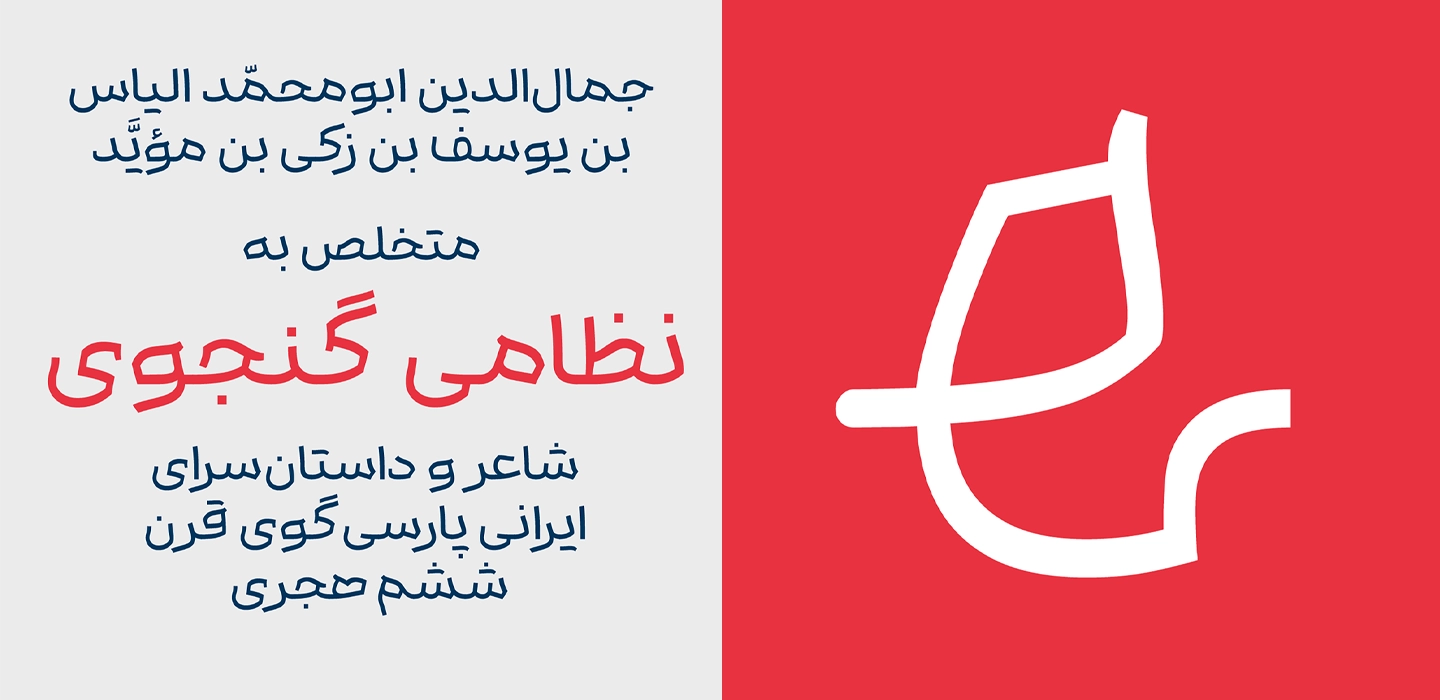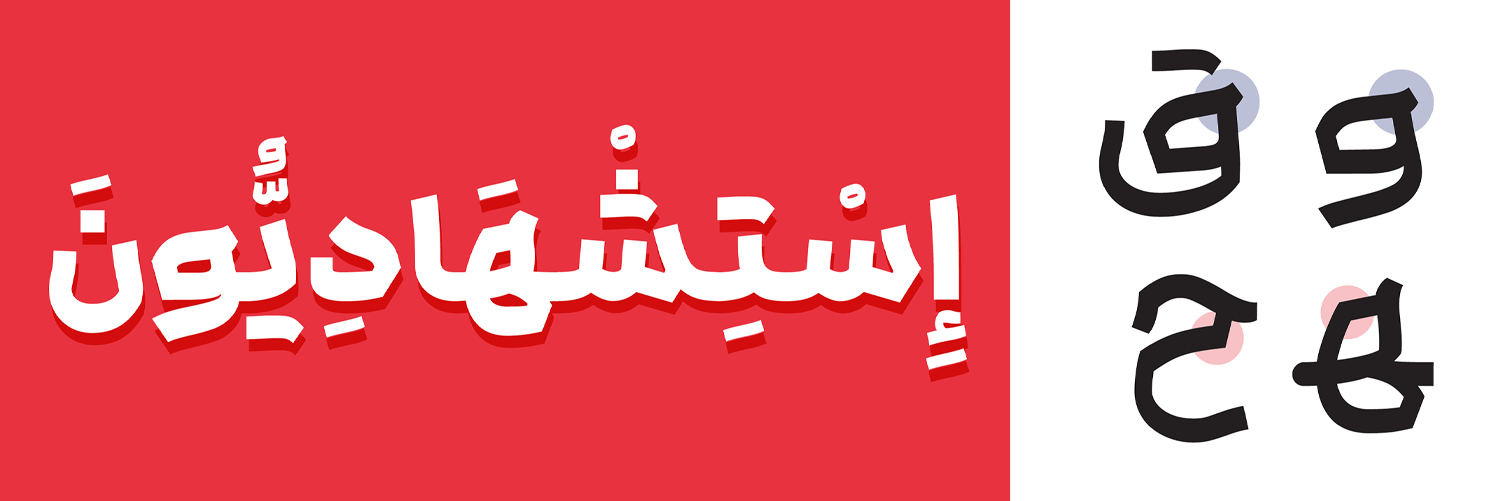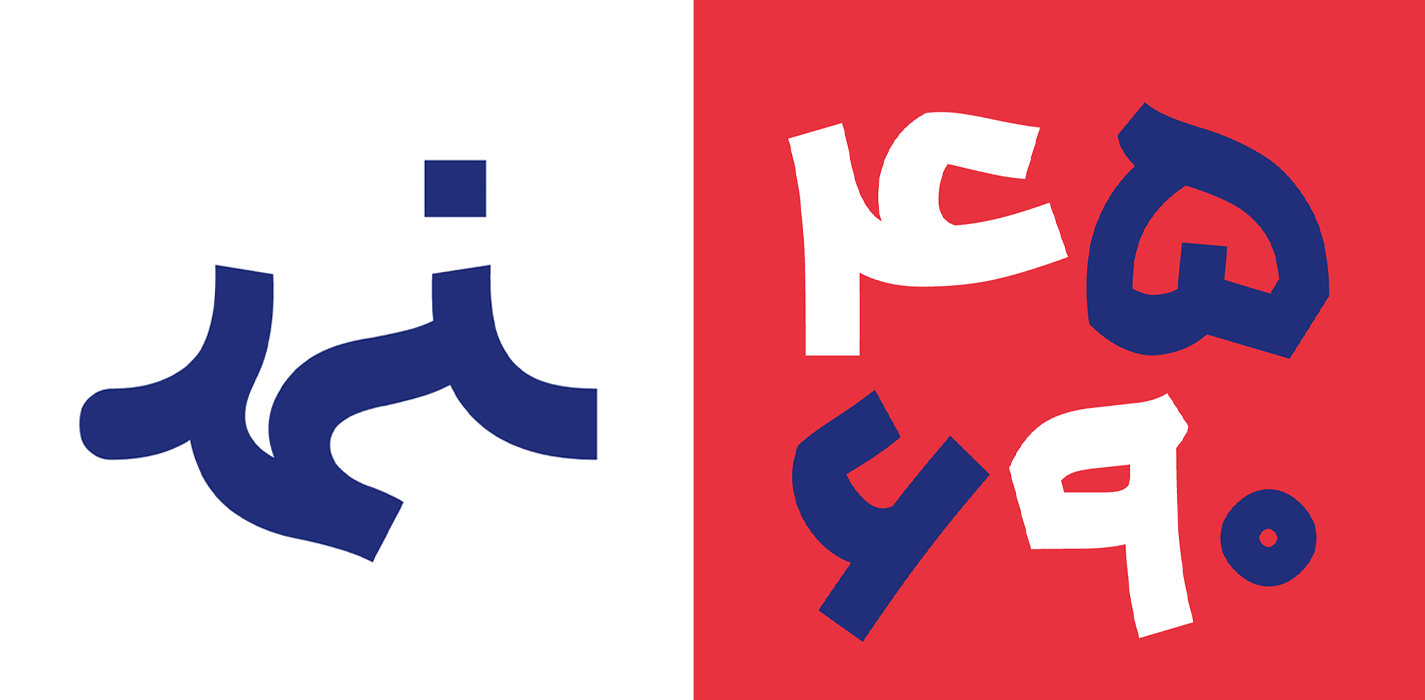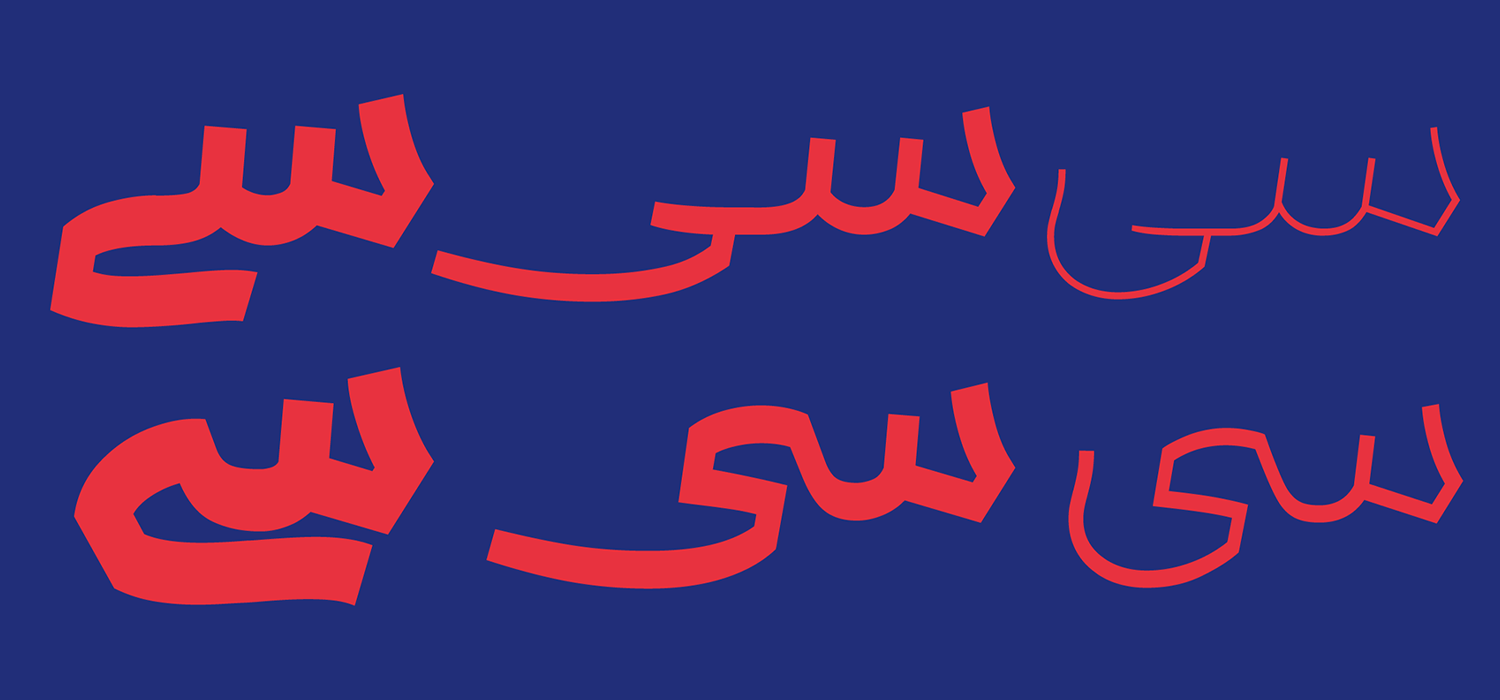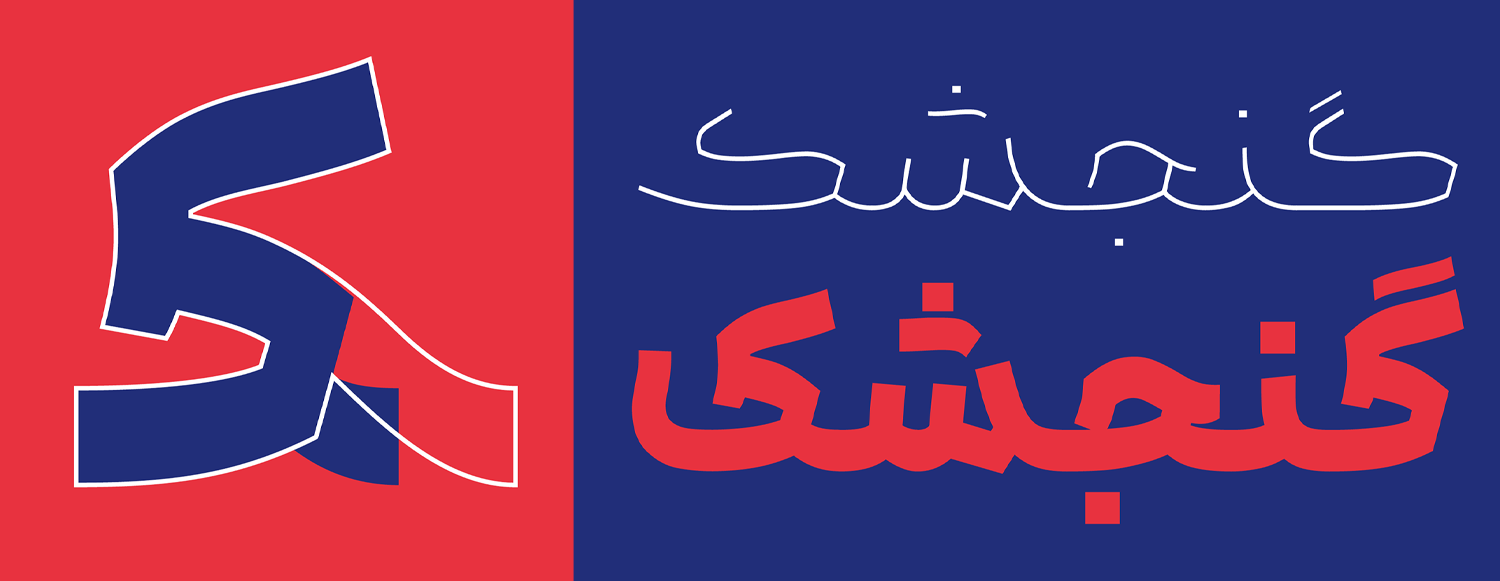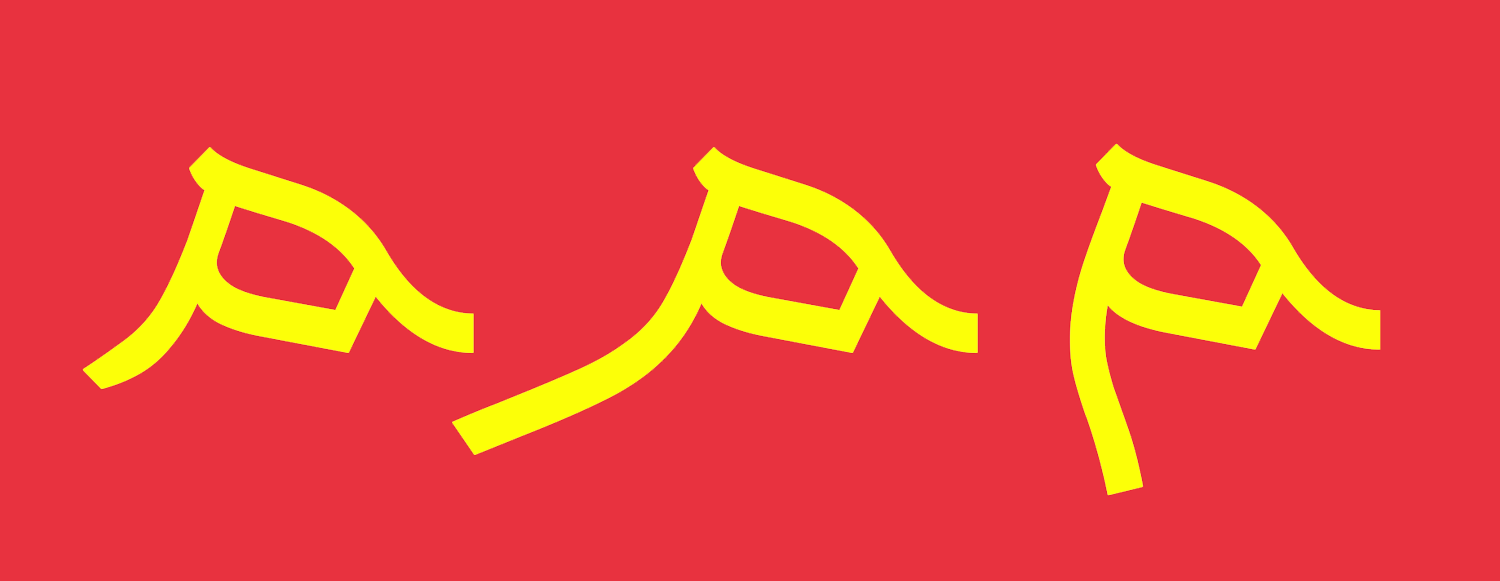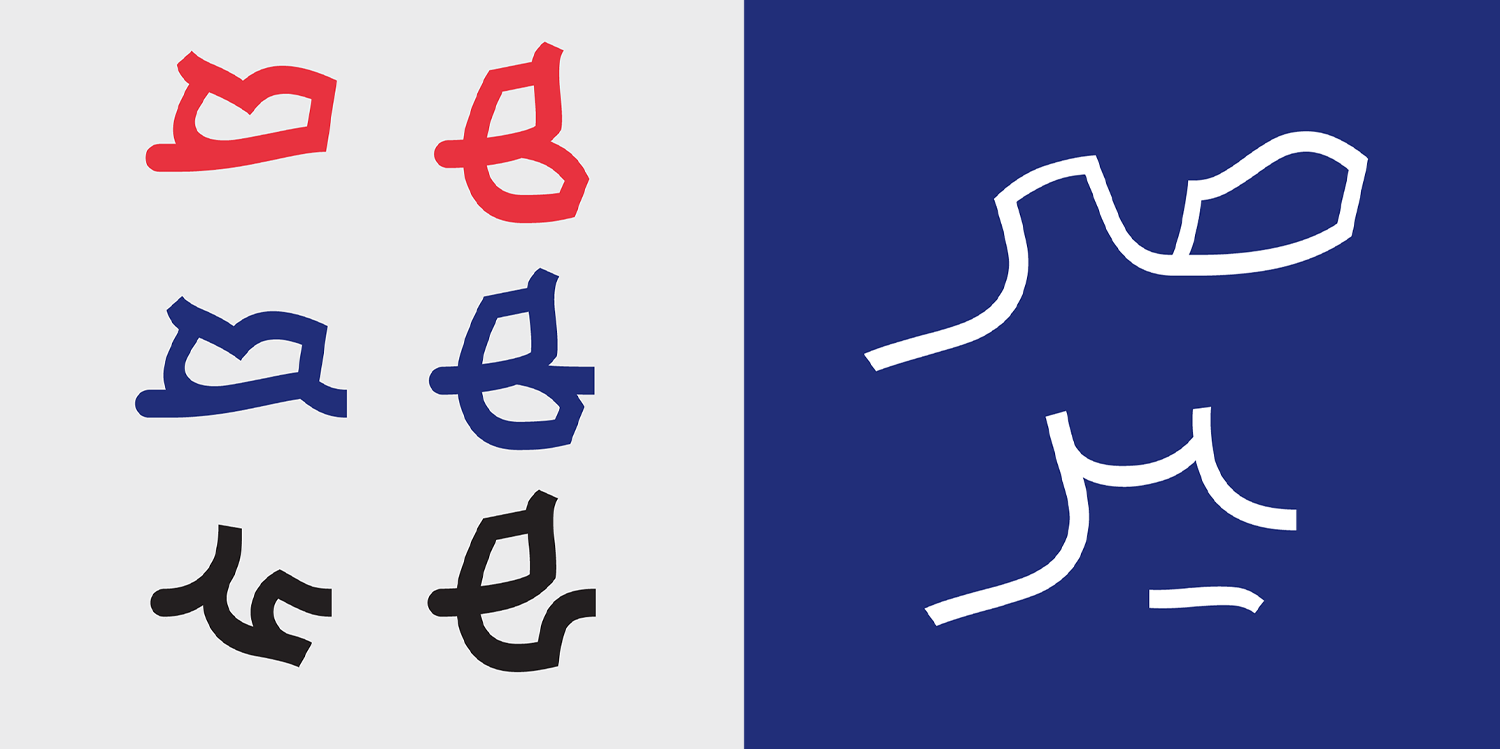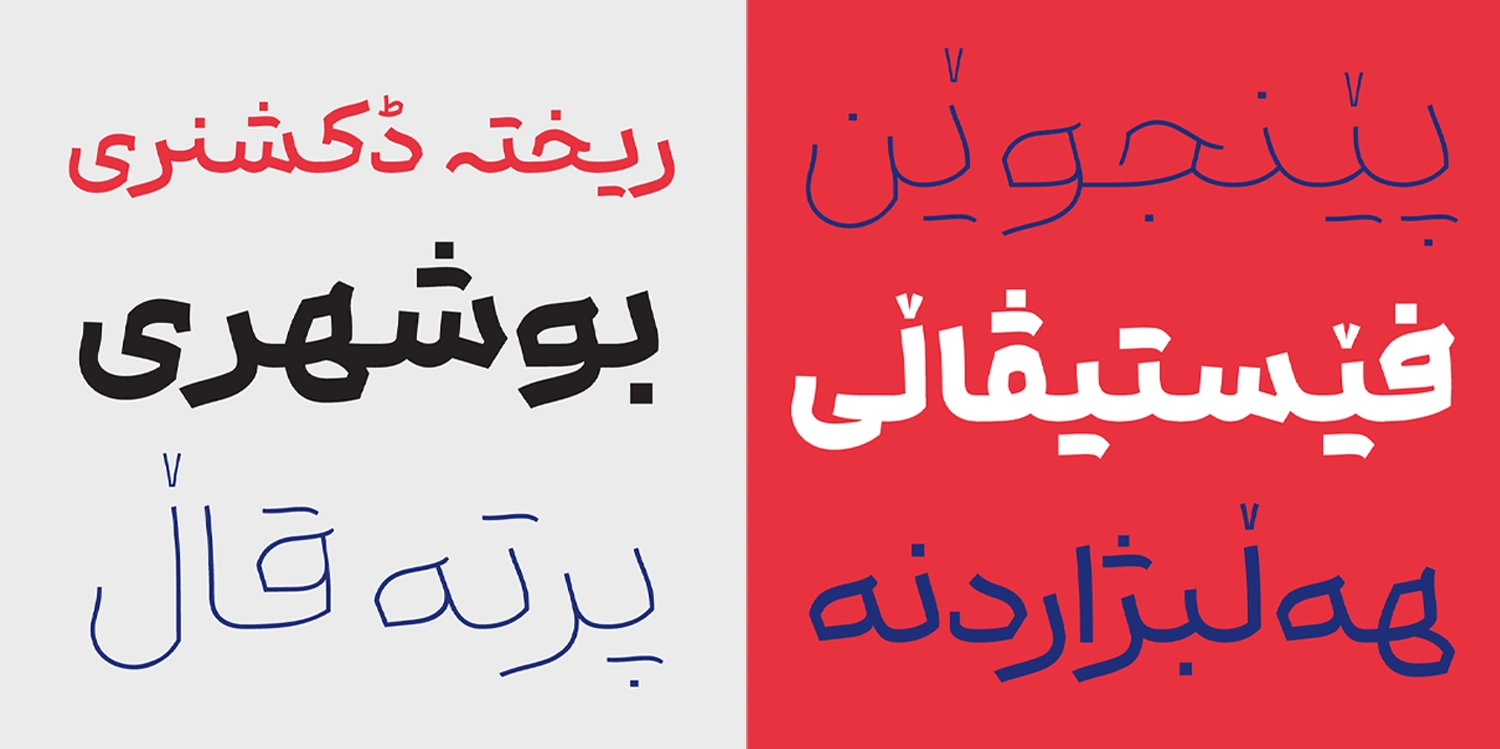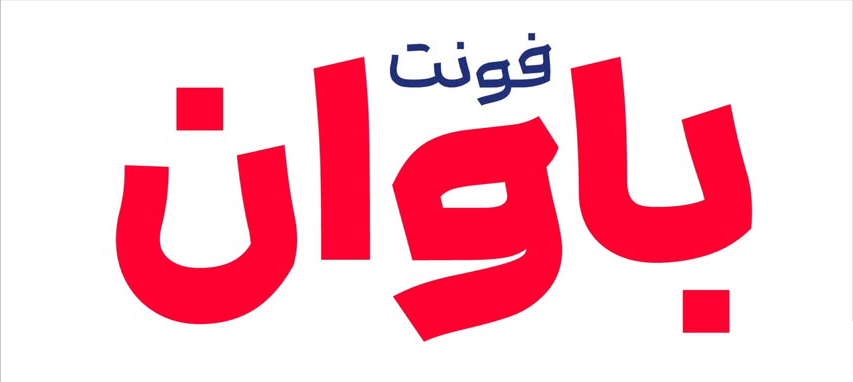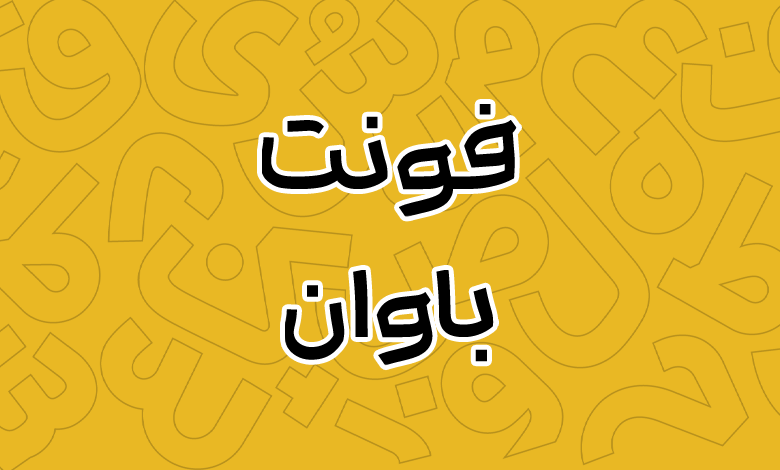
فونت باوان (Bavan)
فونت باوان (به انگلیسی: Bavan) از سری فونتهای هندسی با ترکیبی خلاقانه از خط نسخ و ثلث است. این ترکیب ظاهری صمیمی و در عینحال چهرهای سرشار از برتربینی را در این فونت ایجاد کرده است. از همینرو میتوان برای استفاده در کارهای تبلیغاتی از آن بهترین استفاده را داشت. فونت باوان رایگان نیست و در دو بسته وزنی قابل خریداری است.
ساختار هندسی فونت بهگونهای است که در برخی حروف مانند «م، ح، ف، ق» که شاهد استفاده از چشمی یا گردی هستیم، زائدهای در گوشههای فونت اعمال شده که ظاهر آن را برای تبلیغات نمایشیتر کرده است. خصوصا که خطوط نیز از قانون خاصی تبعیت نکرده و در بخشهای مختلفی شاهد تغییرات جزئی در منحنی و زوایا هستیم.
در ادامه این نوشته از فونتچی به نقد و بررسی فونت Bavan میپردازیم؛ قلمی با ظاهر هندسی و امکانات مناسب که در ۶ وزن عرضه شده و میتواند برای استفاده در عناوین بهویژه تبلیغات چه در فضای چاپی و چه شبکههای اجتماعی تاثیر بسیار چشمگیری روی مخاطب داشته باشد.
پیشنمایش و مشخصات فونت باوان (Bavan)
فونت باوان با ترکیب منحصربهفردی از هندسه مدرن امروزی، ولی با حفظ ظرافتهای سنتی خطوط نسخ و کمی هم ثلث، حس آشنایی و ارتباطی گرم را ایجاد میکند. طراحی این فونت به گونهای است که مخاطب به راحتی با آن ارتباط برقرار میکند و حس حرفهای بودن و خلاقیت را در نگاه اول منتقل میسازد.
این فونت فارسی با ویژگیهای مونولاین (تک ضخامتی) خود، تعادل بصری مناسبی ایجاد کرده و حس نظم و پویایی را در طراحیها القا میکند. فونت باوان انرژی جوان مدرن را در خود دارد؛ گزینهای بینظیر برای استفاده در طراحی پوسترهای تبلیغاتی، پستها و استوریهای شبکههای اجتماعی، و همچنین بستهبندی محصولات مختلف است.
از آنجایی که فونت باوان در دستهی فونتهای مناسب برای متون کوتاه و نیمهبلند است، میتواند بهترین انتخاب برای عناوین باشد که بهدنبال انتقال پیام به صورت واضح و شفاف هستند. انعطافپذیری این فونت، آن را به ابزاری قدرتمند برای برندهایی که به دنبال متمایز کردن هویت بصری خود هستند، تبدیل کرده است.
- پشتیبانی از ۶ وزن متنوع
- این فونت ۶ وزن متنوع نازک تا ضخیم را پشتیبانی میکند. با توجه به مونولاین بودن ساختار حروف، تمامی وزنها دارای ساختاری یکپارچه هستند که میتواند برای طراحی رابط کاربری هم مورد استفاده قرار گیرد.
- این میزان تنوع وزنی، امکان استفاده از هر وزن را برای کاربردهای مختلف طراحی، مانند تیترها، بدنه متون و تبلیغات فراهم نموده است.
در این فونت هرچه وزن افزایش پیدا میکند شاهد ظاهری نمایشیتر و صمیمیتر از فونت هستیم. حتی با وجود اینکه ساختار مونولاین دارد.
- طراحی استاندارد بر اساس هر زبان
- فونت فارسی باوان به لطف رسمخط یکسانی که در زبانهای عربی، کوردی و اردو وجود دارد از این زبانها نیز پشتیبانی کاملی دارد.
- از آنجا که برخی حروف در این زبانها دارای ظاهری متفاوت هستند، گلیفهای خاص هر زبان نیز به فونت افزوده شده است. مانند حروف «ک، ی، ه، ؤ، ئ» در عربی یا «ﮧ، ﮩ، ے» در اردو. همچنین از ظاهر حرف «ے» اردو بهعنوان حروف جایگزین استفاده شده است.
- فونت bavan انگلیسی در حروف لاتین شامل طراحی اختصاصی نیست و از قلم Georama وام گرفته شده است.
در بخش اعداد نیز شاهد رعایت حالت استاندارد هستیم. طوری که اعداد عربی «۰۴۵۶» که متفاوت از اعداد فارسی «۰۴۵۶» هستند گلیف خاص خود را دارند. همچنین در بسته دانلود فونت باوان پوشه مخصوص اعداد فارسی هک شده و فونت مخصوص بدون حروف لاتین نیز قرار گرفته است.
- حروف جایگزین با تزئیات حرفهای
- در فونت باوان شاهد نسخهای خاص از حروف جایگزین هستیم. حروف «ک، گ» فارسی بر خلاف عموم فونتها از دو نوع اتصال برای پیوستن به حروف قبلی خود بهره میبرد.
- سایر ترکیبات از جمله «ـمـ، ـم، ـهـ، ـیر، ـر» نیز دارای چند حالت مختلف در تایپ هستند. راهنمای استفاده از حروف جایگزین در قالب فایل PDF. همراه فونت ارائه شده است.
تمامی این زبانها از نظر اعراب استاندارد هستند. برای زبان کوردی و اردو گلیفهای تزئینی درنظر گرفته شده که میتواند در زمینه تبلیغات به طراحی قلمی بهتر کمک کند.
- ایدهآل برای برندینگ و تبلیغات
- فونتهای هندسی نظیر باوان برای استفاده در تبلیغات و برندینگ گزینهای مناسب هستند.
- ظاهر نمایشی این فونت میتواند برای بستهبندی محصولات مورد استفاده قرار گیرد. خصوصا برای مواد غذایی که با ترکیب رنگهایی مثل قرمز، بهخوبی خودنمایی میکند.
- از این فونت میتوانید برای طراحی استوری و پوستر شبکههای اجتماعی بهره ببرید. چنین فونتهایی سبب افزایش نرخ کلیک میشوند که در دراز مدت به رشد بیشتر صفحه اجتماعی کمک میکنند.
- اگر به دنبال فونتی برای هویت بصری برند خود هستید میتوانید روی این فونت حساب کنید. ظاهری که در نقطهگذاری پیوسته این فونت وجود دارد، حس صمیمیت را بهتر انتقال میدهد.
در پایان لازم بهذکر است که فونت باوان زمانی که در زمینه هویت برند مورد استفاده قرار گیرد، با توجه به تاریخچهای که در سبک طراحی خود دارد میتواند نشاندهنده اصالت و ساختار سنتی در عین ظاهر مدرنیته امروزی خود باشد.
اگر به دنبال یکی از بهترین فونت های اینشات برای تبلیغات هستید، این قلم میتواند جزو اولویتهایتان باشد. سبک خاصی که در زوایای این فونت وجود دارد، جانی دوباره به پوسترهای خلاقانهتان، بهخصوص در شبکههای اجتماعی میبخشد.